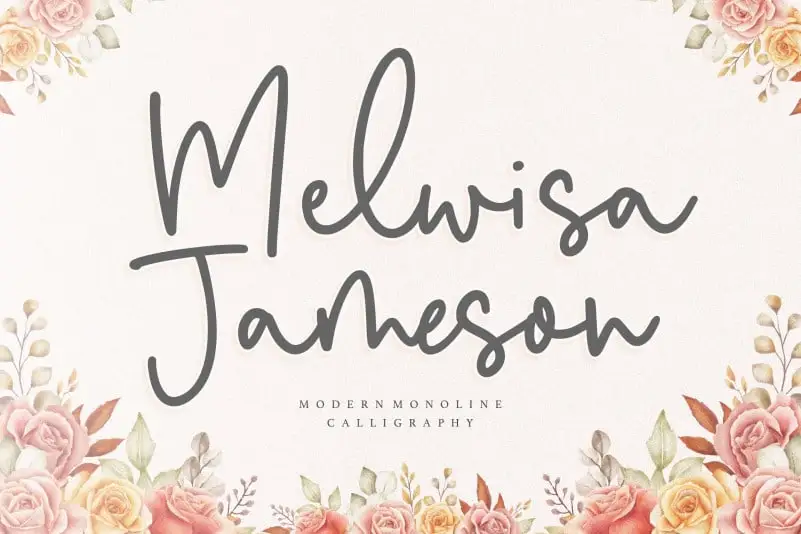
Melwisa Jameson Monoline Calligraphy Font – Download Grátis
A fonte ‘Melwisa Jameson Monoline Calligraphy Font’ é perfeitamente adequada para expressar uma assinatura única e elegante. Seja em aplicativos de redes sociais, embalagens de produtos, criações de marca ou até mesmo para destacar frases sobre backgrounds vibrantes na decoração da sua festa de casamento. Com um traço sólido e detalhado, esta fonte é perfeita para aqueles que desejam dar uma cara personalizada aos seus materiais digitais. Foi projetada pelo designer balpirick e é ideal tanto para pessoas que buscam estilos artísticos quanto aquelas que valorizam o impacto de um texto limpo e elegante em sua identidade visual.